保持简单:徽标的 3 种最佳字体
已发表: 2022-04-16著名的平面设计师 Massimo Vignelli 在 1999 年的一次展览中说: “在成千上万的字体中,我们只需要一些基本的字体。” 他将继续将数字时代越来越多的字体称为“威胁我们文化的新水平的视觉污染”。
虽然你可能不知道他的名字,但你可能已经看过他的作品。
Vignelli 对现代设计文化的贡献是无与伦比的,他的指纹遍布我们组织视觉信息的整个过程。 他反复出现的美学比喻依赖于现代性和简单性的租户,将时尚的几何视觉注入他的设计中。 结果? 永恒。
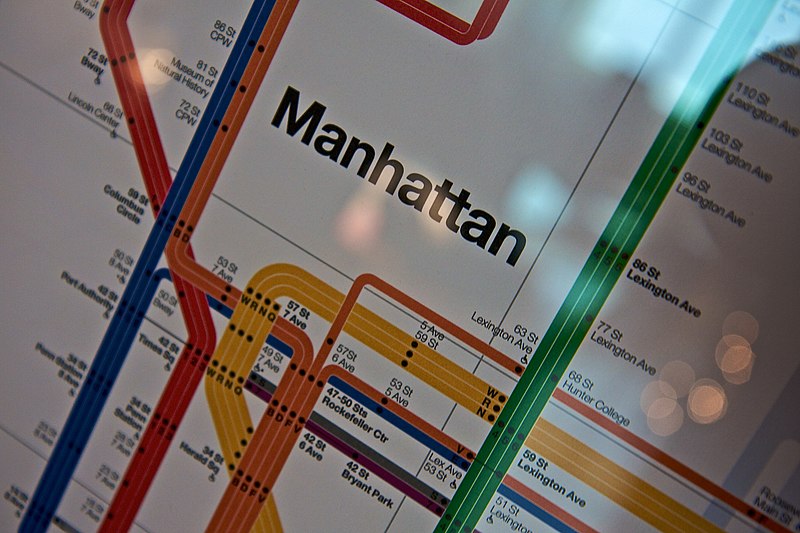
例如,纽约地铁标牌有一些无限酷的东西,由 Vignelli 于 1972 年设计。只有城市方面故意的审美偏离才会使他的作品脱离即时性和有效性的最高梯队。
但即使在他所有的胜利,历史上的荣耀中,你质疑这样一个大胆的主张也是正确的。 我的意思是,只有几个基本字体? 这会让我的品牌得到推广吗? 如果我只依靠传统的品牌推广路线,我怎么能脱颖而出? 你问这些问题是对的,但让我们考虑一些事实:
1) 世界上许多最知名的品牌都使用三种最常见的字体之一,以及 2) 你可能从来没有意识到有多少品牌在他们的品牌中使用完全相同的字体。
徽标的最佳字体?
在品牌推广中,商业文字商标是一种基于字体的徽标,专门针对企业名称。 由于它依赖于书面文字,一个好的字标设计需要对排版有很好的理解。
今天,我们将讨论一些最容易识别的品牌字体,深入研究它们的工作原理,并询问为什么这么多成功的企业几十年来一直使用相同的少数字体。
很容易假设,仅仅因为你想让你的标志脱颖而出,你就必须变得大而多彩,轻松地将你的名字与设计相似的标志人群区分开来。 但是,显然情况并非如此。 某些字体长期以来一直对标志设计的束缚是有原因的。 其中许多自 20 世纪中叶以来就已经存在。
Massimo Vignelli 明确命名了他的五种字体:Futura、Helvetica、Times New Roman、Bodoni 和 Century。
但这篇文章不是关于 Massimo Vignelli 或他特定的排版偏好。 直到今天(包括今天),现代历史上的大量品牌都轻松地依赖于一些精心设计的字体。 几十年来,以下字体一直是标志设计的中流砥柱。 以下是一些共享这些字体的最知名品牌。
前卫哥特式
Avant-Garde Gothic 是由 Herb Lubalin 和 Tom Carnase 设计的几何无衬线字体。 它最初用于 1968 年 1 月至 1971 年 7 月出版的 Avant-Garde 杂志。此后,它进入了无数公司的设计库。
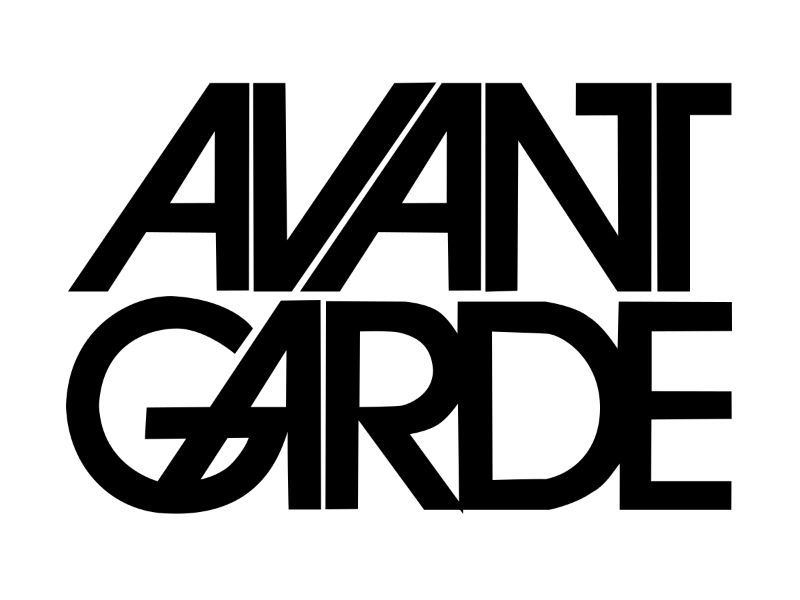
阿迪达斯
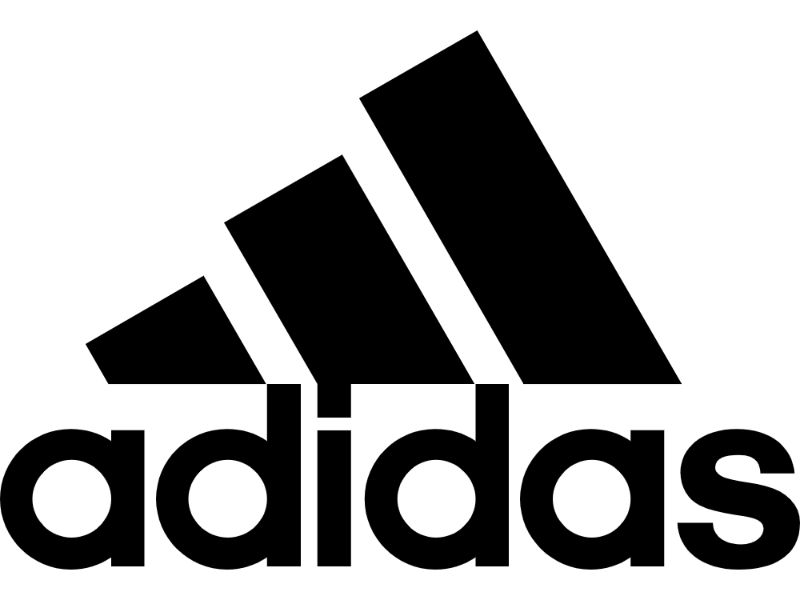
也许阿迪达斯标志最引人注目的部分是其获得专利的三条纹。 然而,它使用大胆的前卫字体作为伴随文字标记,使阿迪达斯标志发展成为一个永恒的标志,并且成为有史以来最容易识别的品牌之一。 这种字体厚实、低对比度的笔触与其标志的大胆、鲜明的条纹相得益彰。
布卢明代尔
Bloomingdale's 使用了更薄的前卫哥特式风格,此外还对某些角色进行了一些轻微的定制。 这有助于在部署经过验证的真实字体时创建新的标识。
梅西百货
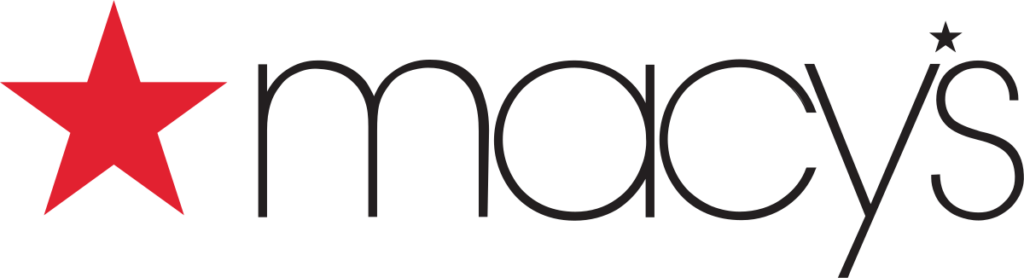
您可能会惊讶地发现梅西百货实际上拥有 Bloomingdale's。 更令人惊讶的是,两家公司自 1970 年代以来一直在使用非常类似于 Extra Thin Avant-Garde Gothic 的字体。 在梅西百货于 1994 年收购 Bloomingdale's 之前将近整整两个十年。
美孚
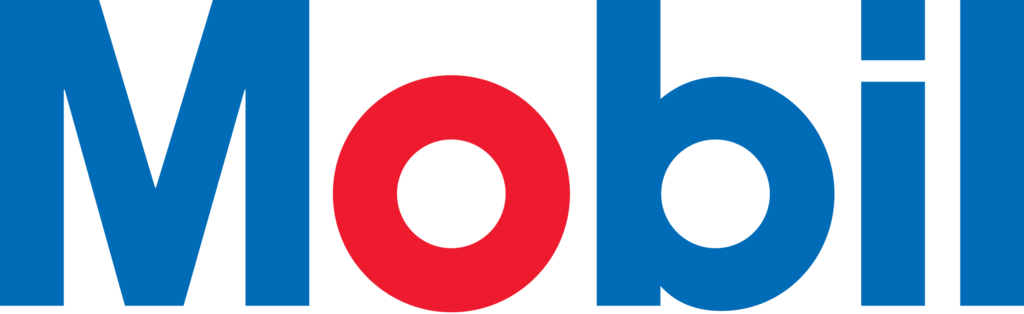
美孚石油自 1964 年以来一直使用相同的标志和字体,当时它是由广告集团 Chermayeff 和 Geismar Inc. 的 Tom Geismar 设计的。
花生酱
自 1964 年决定改用前卫哥特式以来,这个标志性的意大利榛子品牌同样依赖于几乎未受影响的印刷设计。
富利
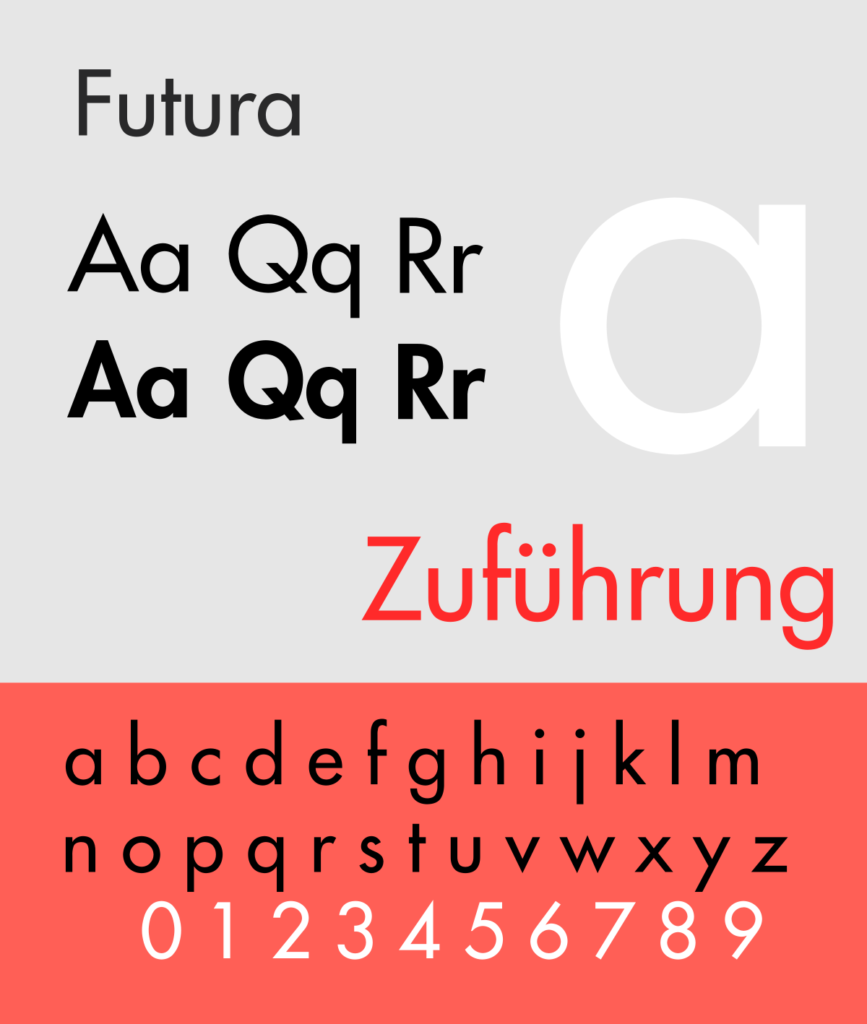
另一个进入文字商标历史史册的几何无衬线字体是 Futura。 Bauer Type Foundry 最初设计为对新法兰克福项目的贡献,于 1926 年开发了它。它在首次出版时领先于时代,并在近 100 年后保持其现代有效性。 以下是一些同意的企业!
百思买
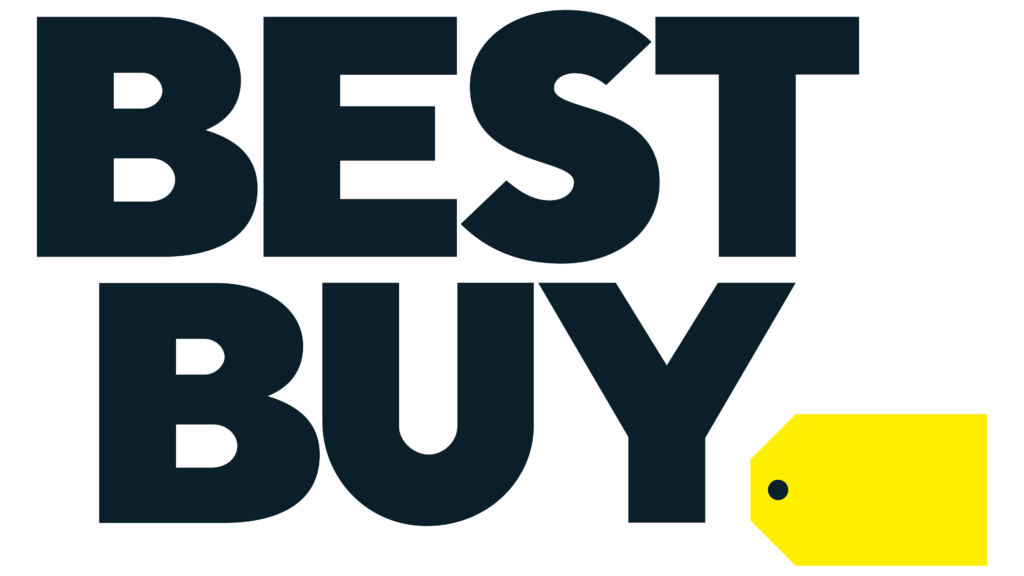
不久前,百思买一度接近卓越零售的前沿。 近年来,它进行了品牌重塑,其中包括重新设计徽标。 但该公司已决定继续使用 Futura。
多米诺骨牌
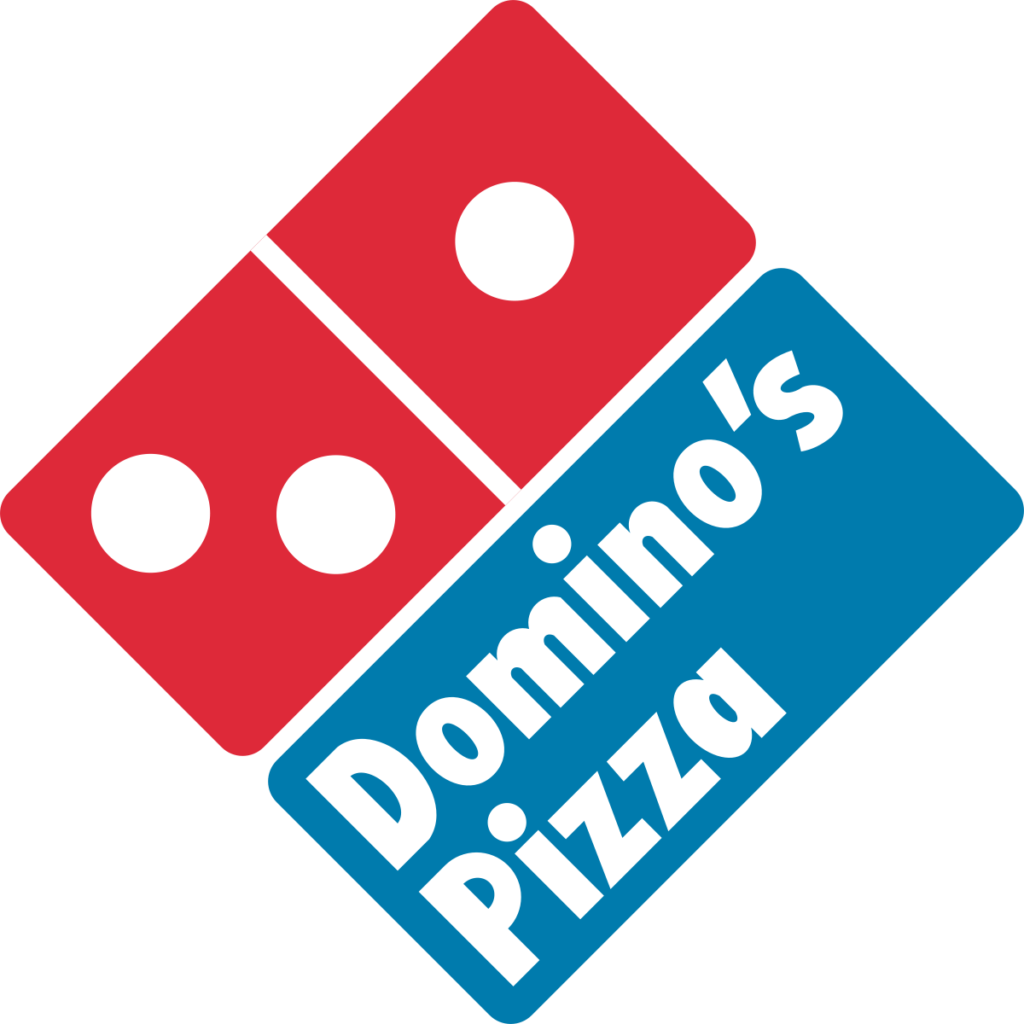
从电子产品零售商迅速转变为比萨连锁店! 但说真的,这种多功能性怎么样。
联邦快递
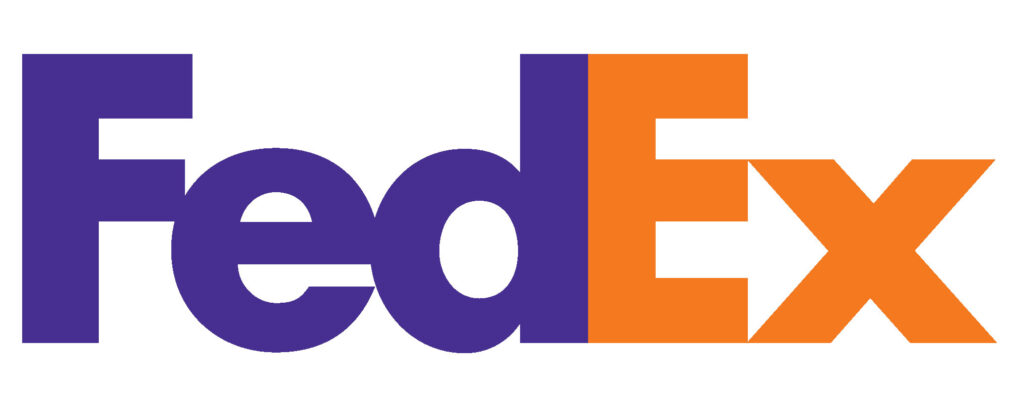
联邦快递的标志很有趣有几个原因。 不仅有著名的潜意识箭头隐藏在 E 和 X 之间的负空间中,而且 FedEx 字标实际上是由两种不同的字体组成的。 Futura and Univers 67. 但它的大部分特点是 Futura 的所作所为。
去资助我
Go Fund Me 是一家相对较新的公司,成立于 2010 年。但即使是较新的品牌也发现他们的身份通过这个永恒的经典得以最好地表达。
耐克
耐克几乎是一个无处不在的品牌名称。 它的字体被简单地称为“耐克字体”。 实际上,这只是 Futura 的另一个例子。 但其字标的斜角及其专利的“swoosh”摘要赋予耐克标志独特的氛围。
黑尔维提卡
Helvetica 由 Max Miedinger 设计,并于 1957 年由 Linotype 出版。它被称为“基准 sans”,被认为是平面设计的永恒主食。 多年来,已经开发了许多变体,包括不同的重量、宽度和尺寸。 它坚固的几何简单性使其成为徽标的最佳字体之一。 无数品牌都依赖于 Helvetica 的时尚即时性。
美国服装
American Apparel 不仅选择使用 Helvetica,而且他们强烈地感受到它具有可靠性、时尚性和现代性的能力,以至于他们没有调整任何东西。 这包括颜色,假设我们认为黑色是默认字体颜色。 打开任何文字处理器,选择 Helvetica,然后输入 American Apparel,您将拥有他们的文字标记。 图形天才。
吉普车
吉普一定也有同样的感觉。
LG
LG有一个很好的组合标志。 徽标建议使用公司字母的笑脸。 但他们的字标使用简单的灰色 Helvetica 粗体字体。
松下
不知何故,松下在坚持印刷基础的同时仍然毫不费力地辨认出来。
目标
塔吉特的标志已经改变了好几次。 早期的迭代包括斜体字体、各种案例和大量不同的靶心设计。 但自 60 年代后期以来,Target 一直使用 Helvetica Neue 作为其文字标记。